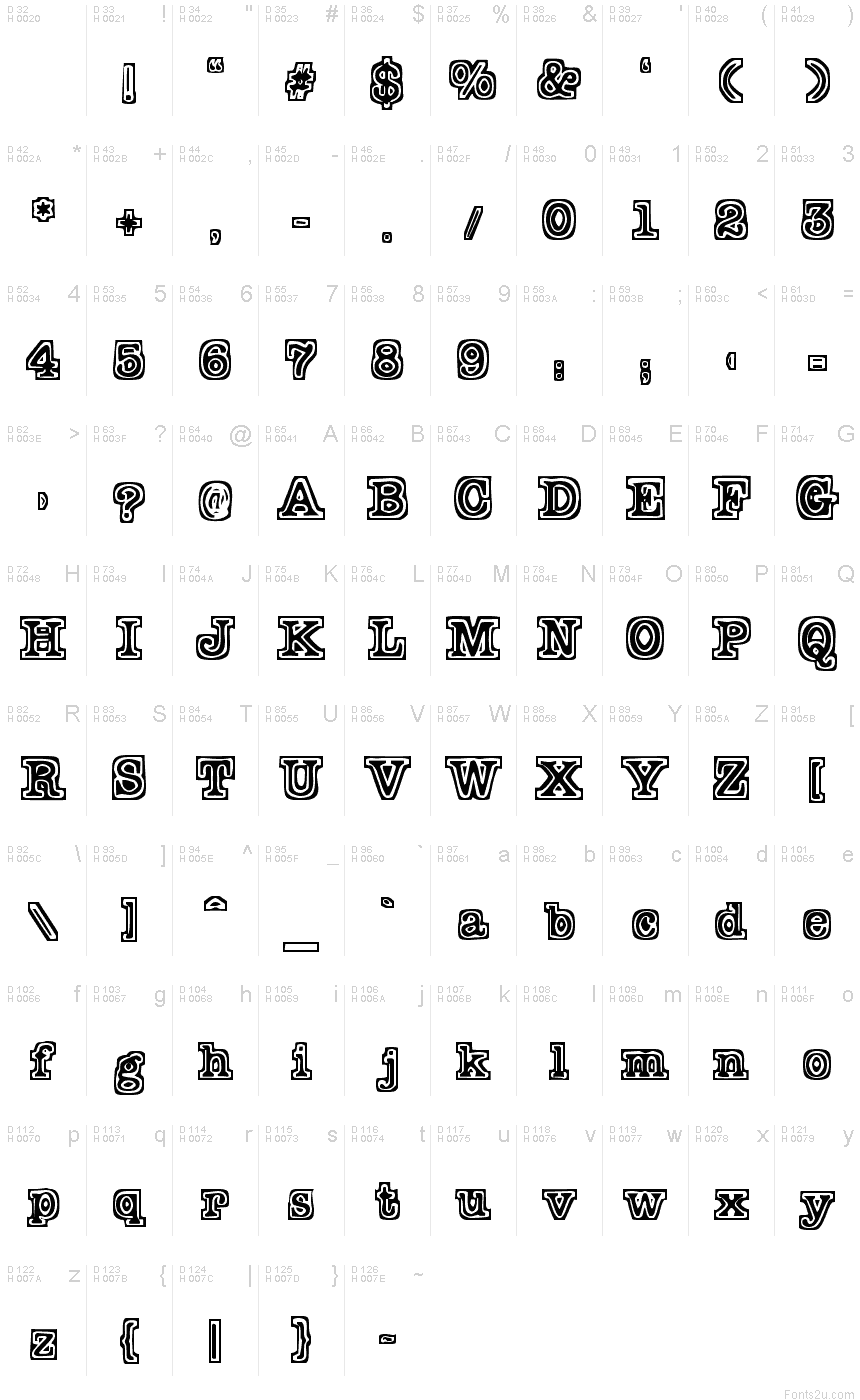
TypeBlock 字体
TypeBlock
Sunwalk Designs
Andy Krahling
Type Block 由 Sunwalk Designs 设计,是一款复古风的免费轮廓显示字体。它具有类似木活字的厚重字母,以及一种如同手工切割般略带生涩的质感。字体造型大胆紧凑,但双线边框和圆润的边角处理使其整体风格俏皮而不严肃。
非常适合海报、书籍封面、包装、标题和标志设计,如果您想要营造老式招牌的复古感,却又不想显得过于“西部片”,这款字体是理想选择。作为一款免费字体,它也非常适合短标题和类似字母组合的设计,其厚重的轮廓和空心设计,即便只有几个字母也能带来极强的视觉冲击力。